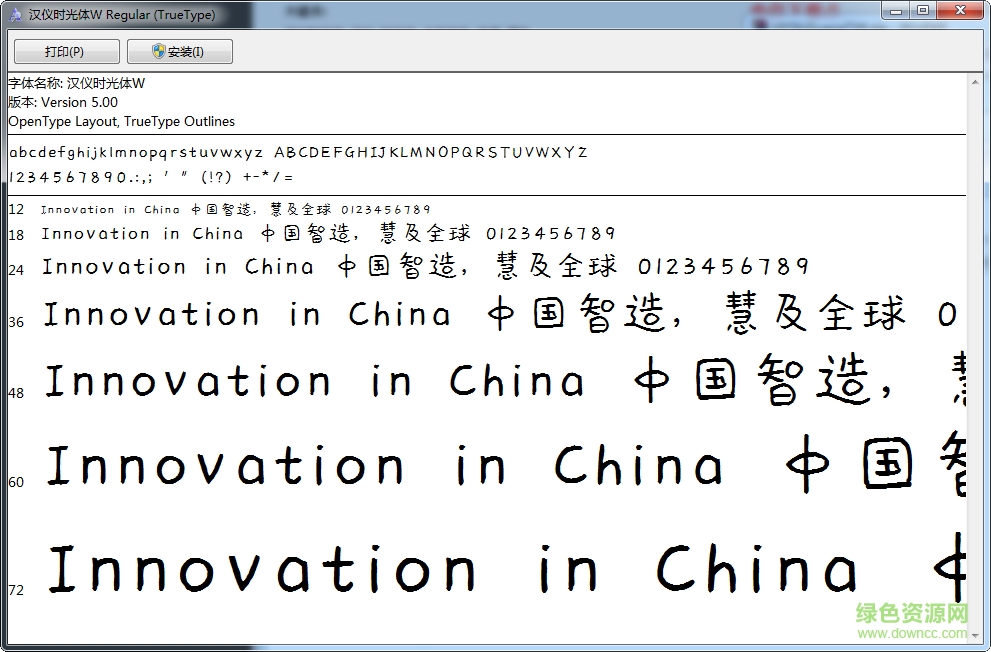
漢儀時(shí)光體是一款具有手寫風(fēng)格的卡通字體,字體乖巧可愛,趣味性強(qiáng),收錄4522個(gè)中文字符,覆蓋面超過99.96%,另包含英文和常用標(biāo)點(diǎn)符號(hào),滿足大陸地區(qū)日常所需。適用于兒童食品包裝、繪本文字、兒童玩具廣告等設(shè)計(jì)場(chǎng)合使用。歡迎來綠色資源網(wǎng)下載。